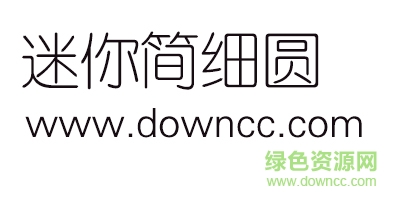
迷你簡細(xì)圓是迷你字體庫中的一種經(jīng)典字體,本字體完全免費(fèi)使用!這款字體適合用于藝術(shù)策劃、廣告制作等方面,使用范圍非常廣泛!喜歡的朋友們歡迎來綠色資源網(wǎng)下載體驗喲!
迷你簡細(xì)圓是一款應(yīng)用于設(shè)計方面的中文簡體漢字,該字體纖細(xì)大方得體,整體風(fēng)格非常出色,并且字庫完整,可以適用于名片設(shè)計、平面設(shè)計、廣告設(shè)計、報紙雜志等領(lǐng)域。
1.字體清晰、端正、嚴(yán)肅
2.拐角處、筆畫末端為圓弧狀